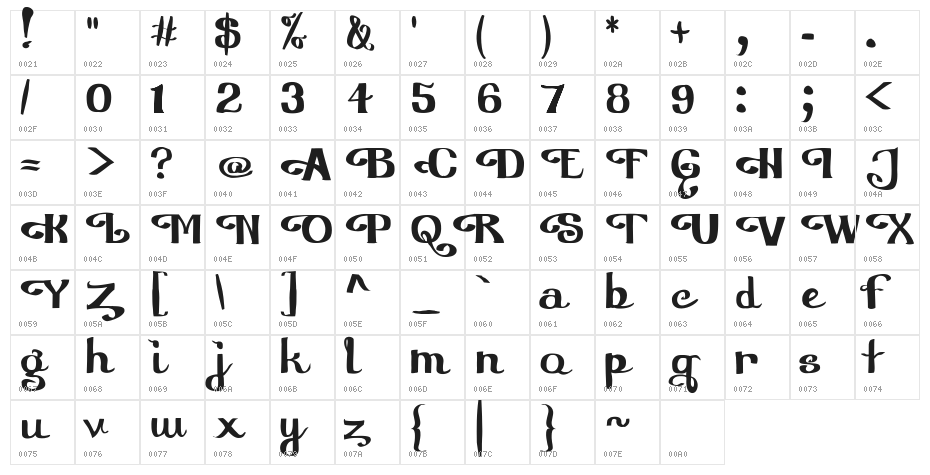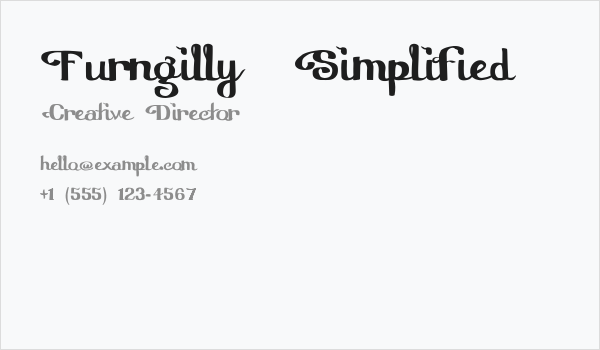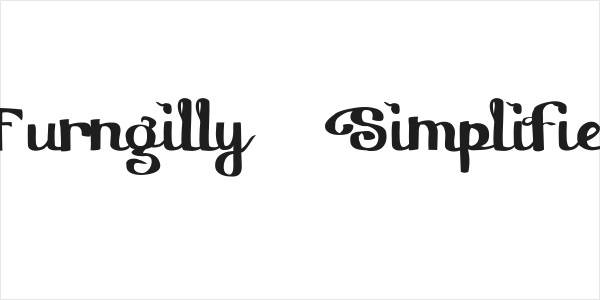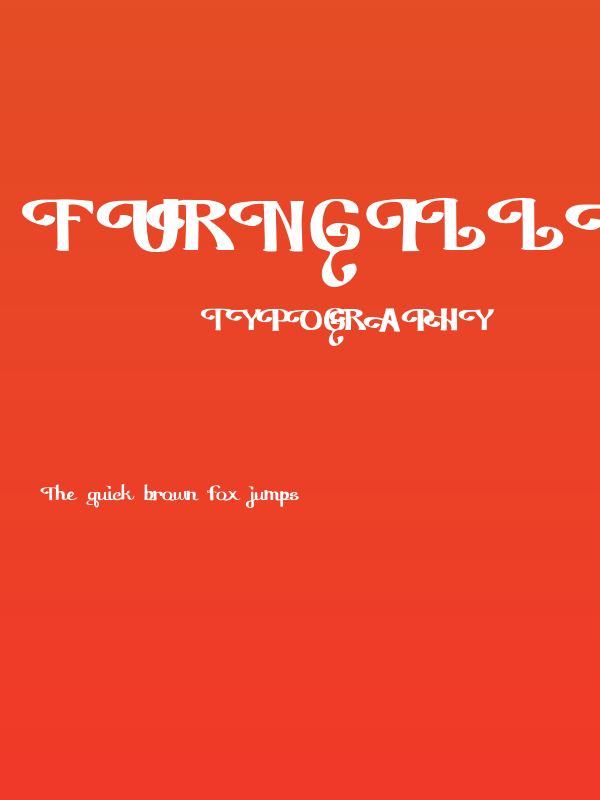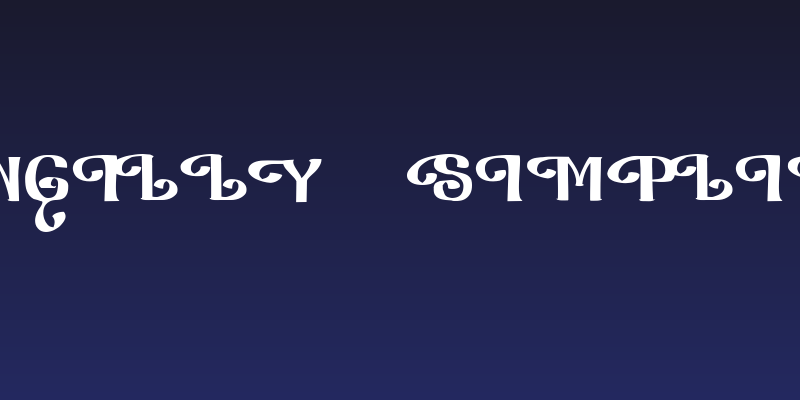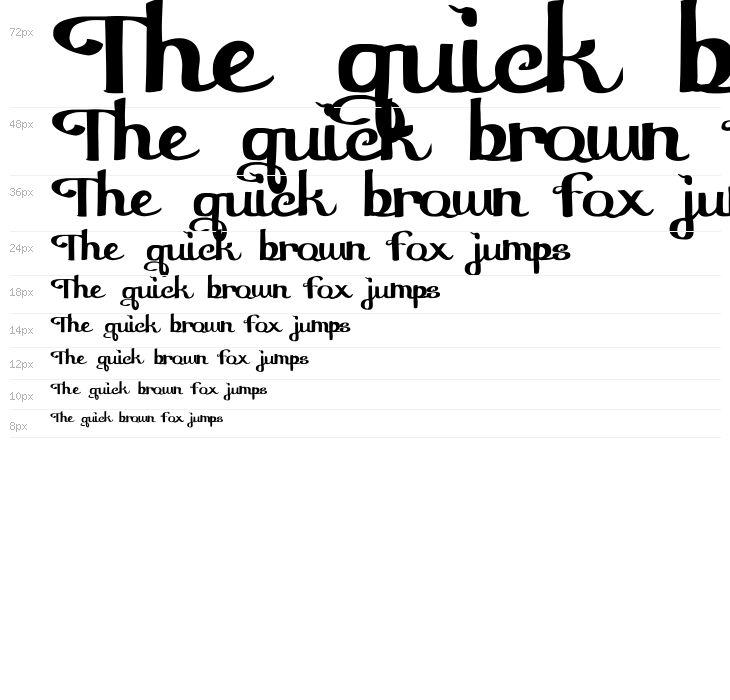
Furngilly Simplified Font
| Caso d'uso | Headlines, Logos, Invitations |
| Progetti proposti | Ideal for invitations, posters, branding, and any project needing a creative and elegant touch. |